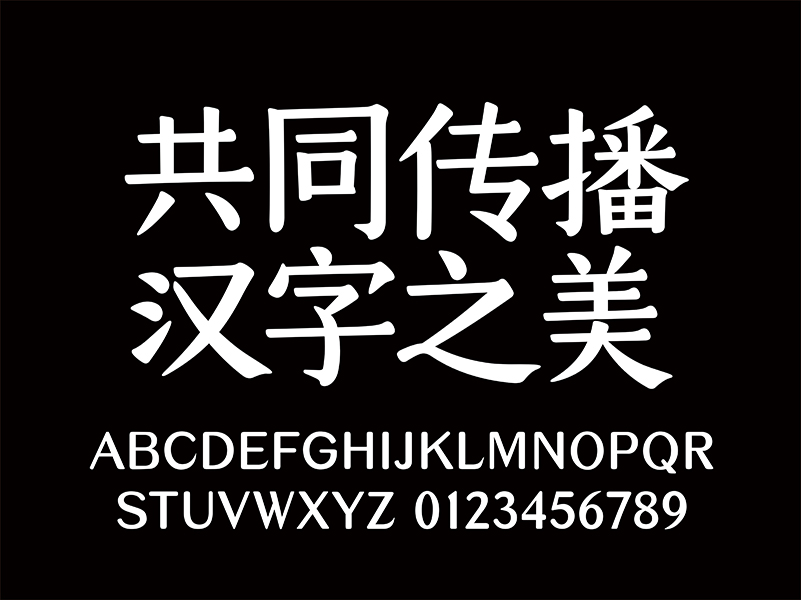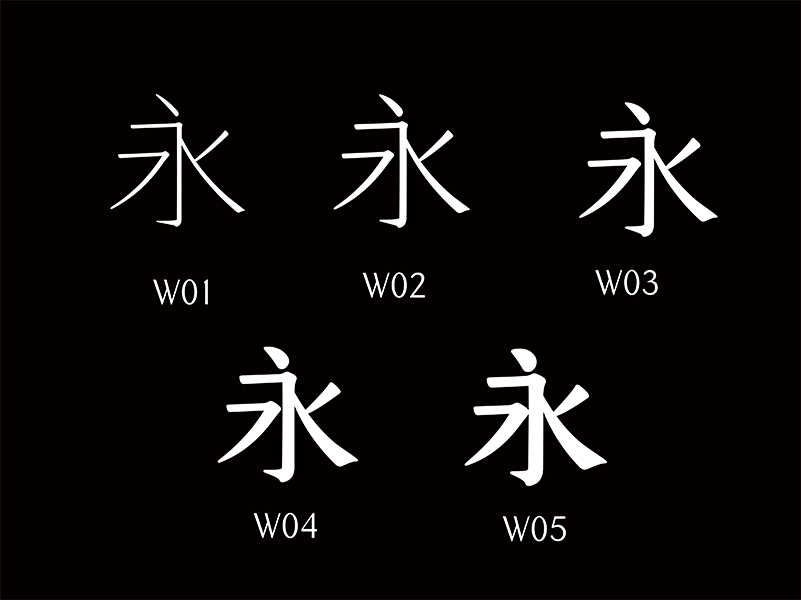
(仓耳谷力04家族字体)仓耳羽辰体W02
(仓耳谷力04家族字体)仓耳羽辰体W02,仓耳羽辰体这款家族字体,分6个字重,结合了楷体与玄三的笔形特点,结构上适当做了不匀称调整,将横划调细,并且在横划末端增加了圆弧形凸起。稍有不协调字形结构使字体增加了几分可爱之气,形成了字体独有的风格。字体拥有五个字重,可根据不同应用场景自由选择。。